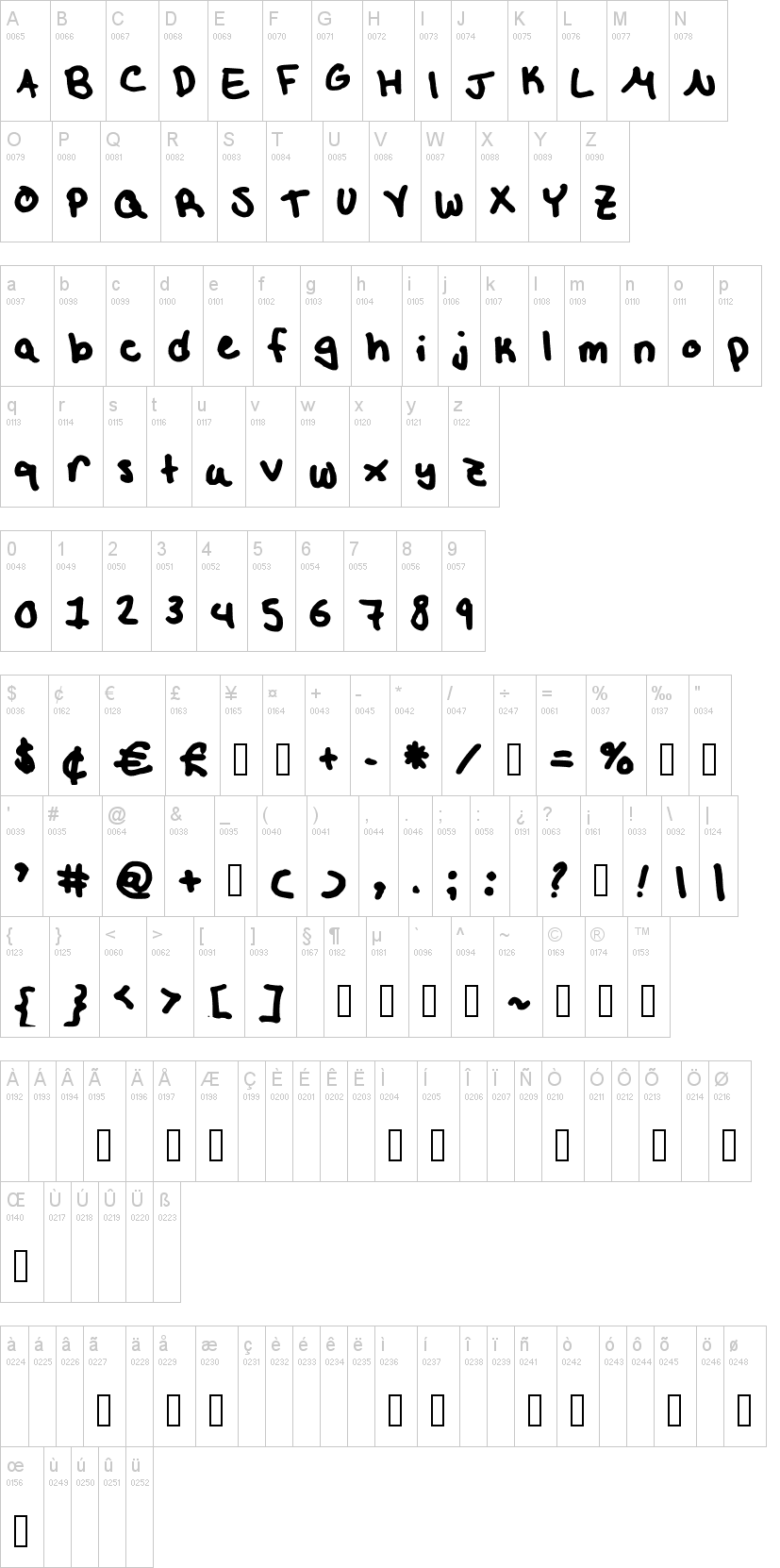
Etw 字体是一款由品牌设计公司 TypeTogether 设计的有机无衬线字体。其名字来源于“Elastic Type Works”的缩写,意为弹性字体工作。该字体于2013年发布,是 TypeTogether 公司的一项创新成果,采用了先进的 OpenType 技术。 Etw 字体具有硬朗、有力的设计风格,其字形有机而自然,让人联想到细胞、肌肉和骨骼等有机元素。相比传统的无衬线字体,Etw 字体更加灵活,具有更多的变形功能和个性特点。 Etw 字体包含 6 种不同的字重,各种字重都有着相同的精美设计,可以适用于不同的设计需求。该字体还具有多国语言支持,包括拉丁字母、希腊字母、西里尔字母和越南语等。Etw 字体适用于各种设计应用,如印刷品、标志和品牌设计、数字设计等。内容介绍
Etw是一款非常不错的手写艺术字体,具有很好的视觉感,适合于文化类的宣传设计、商业类品牌的广告和产品包装设计以及个性化文字排版等较多场景。